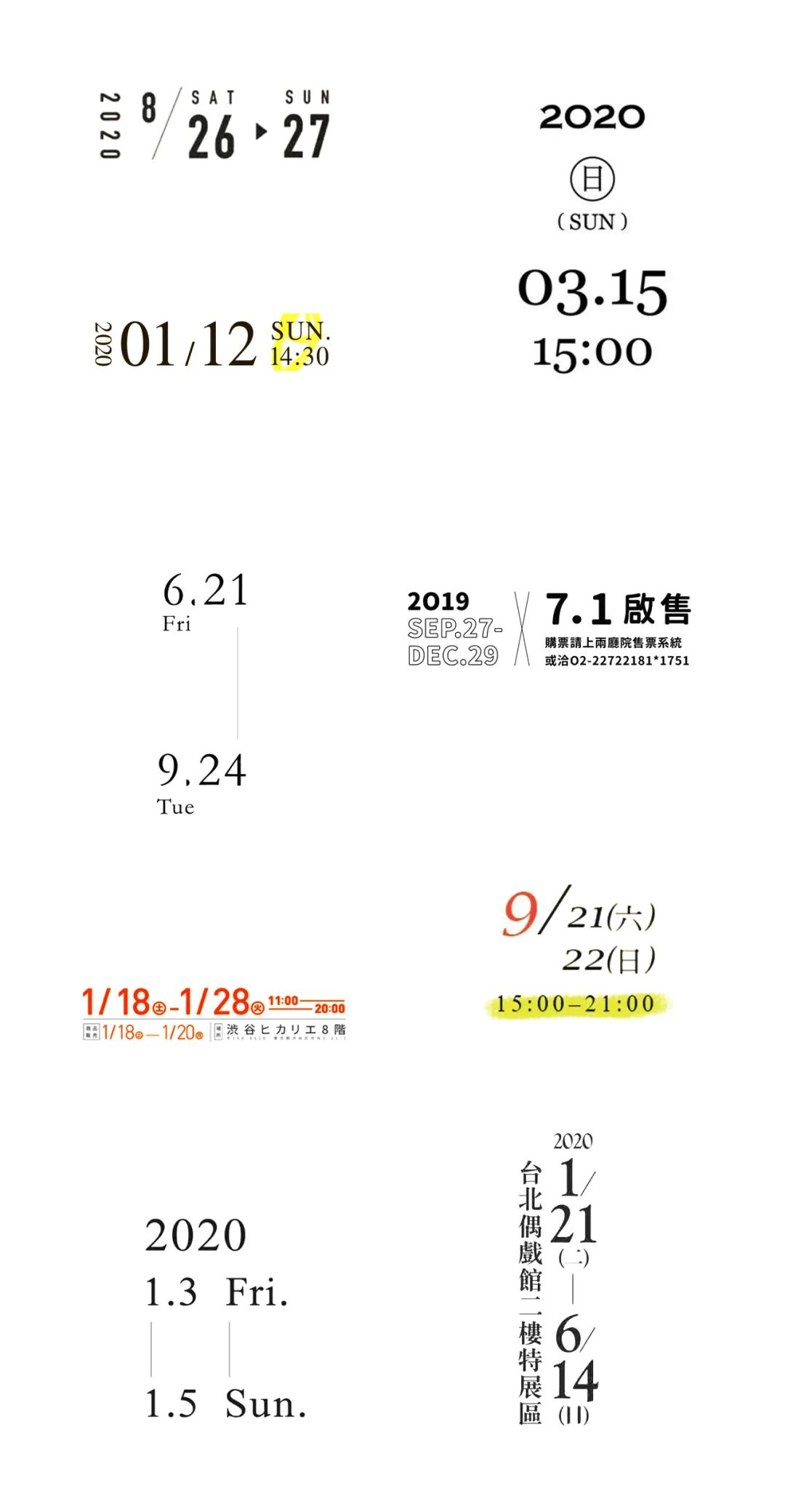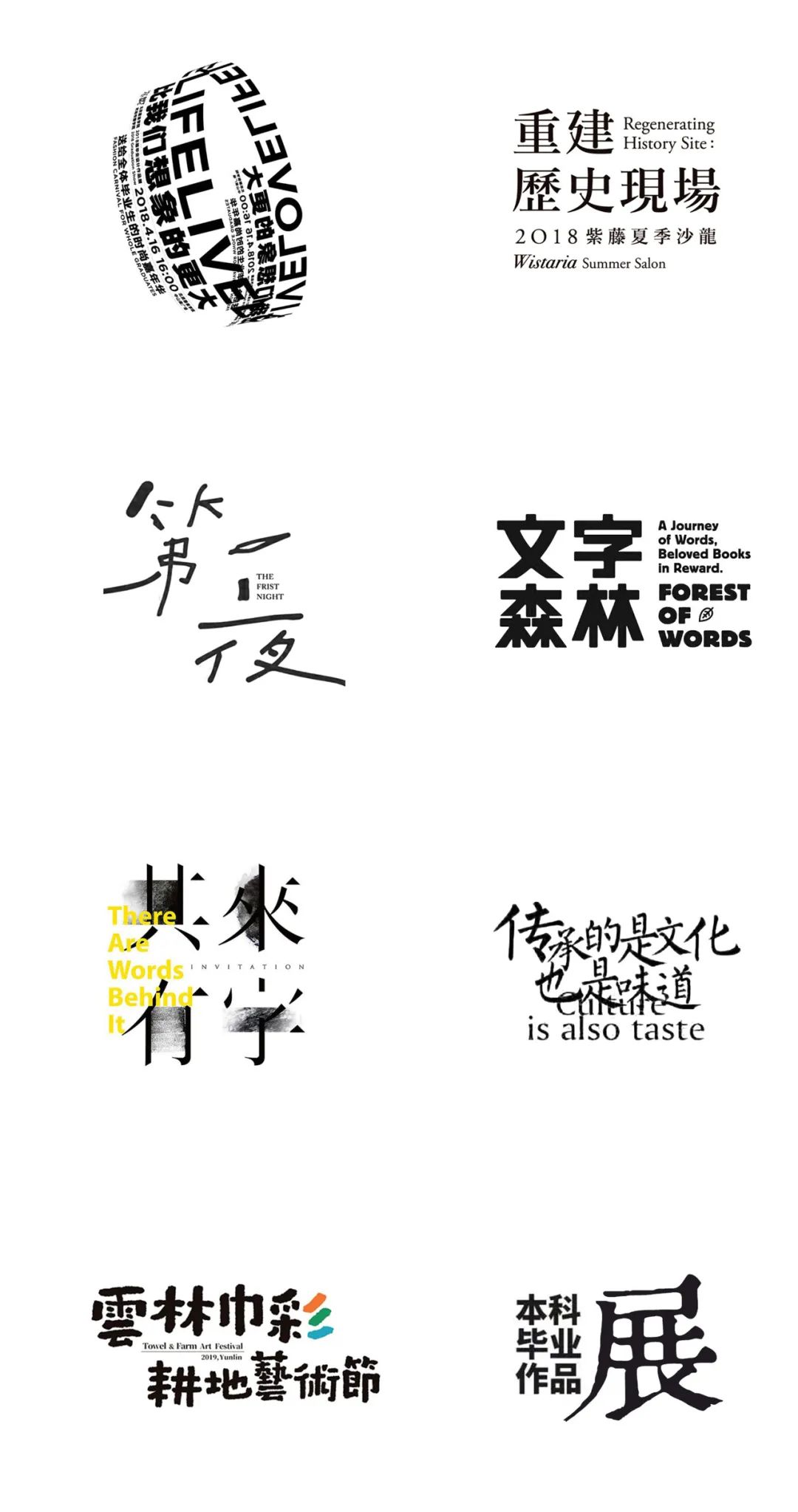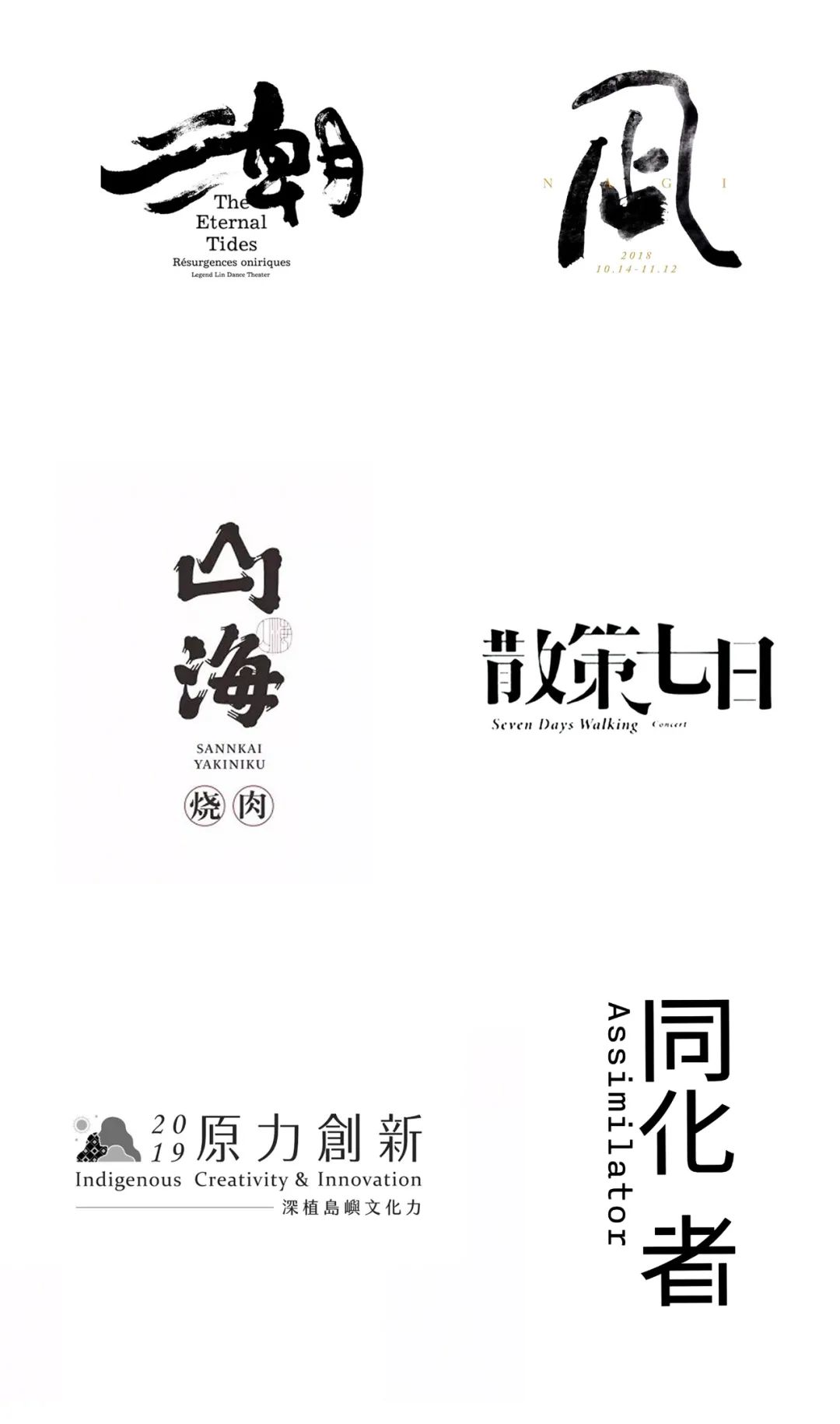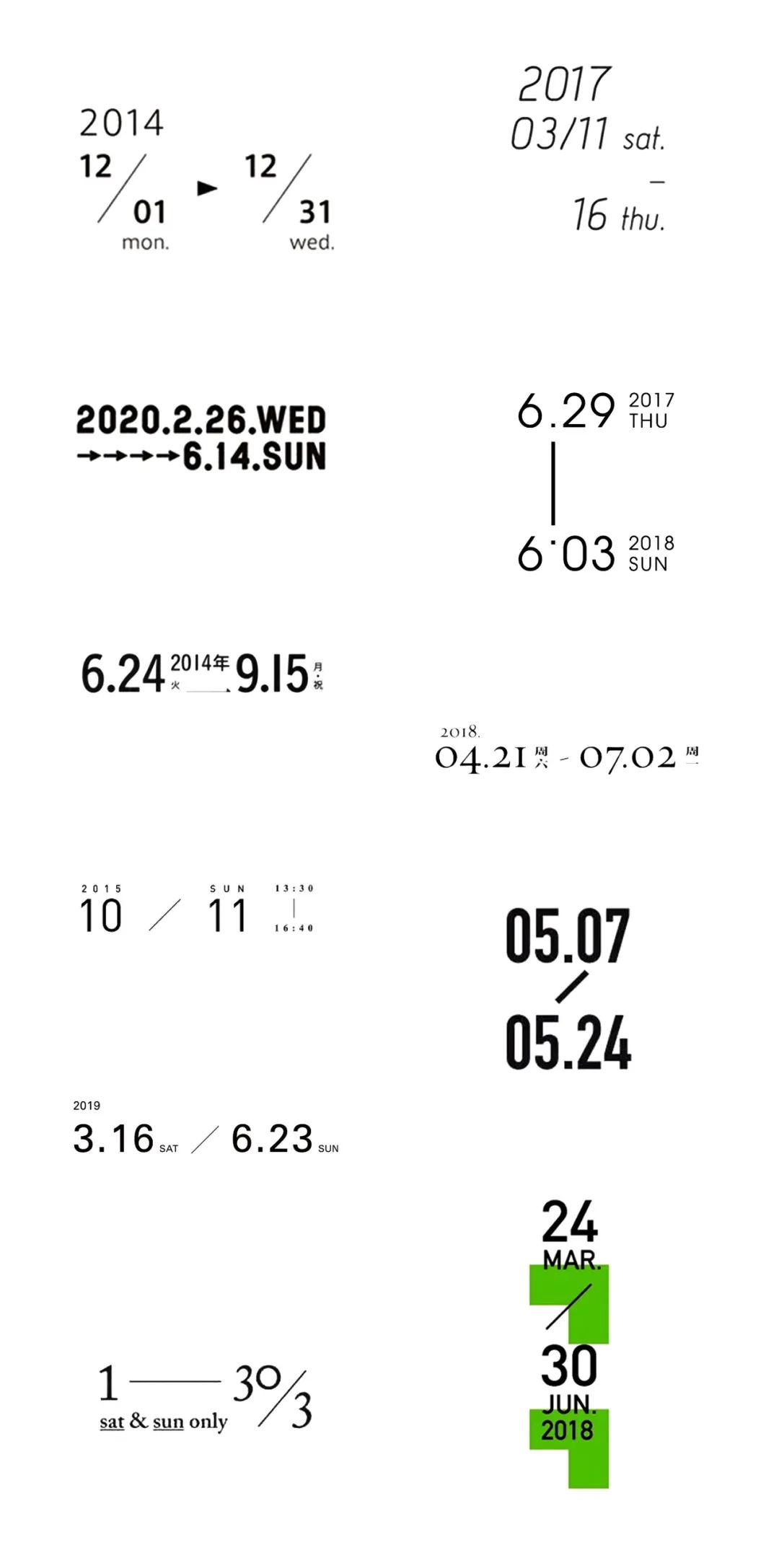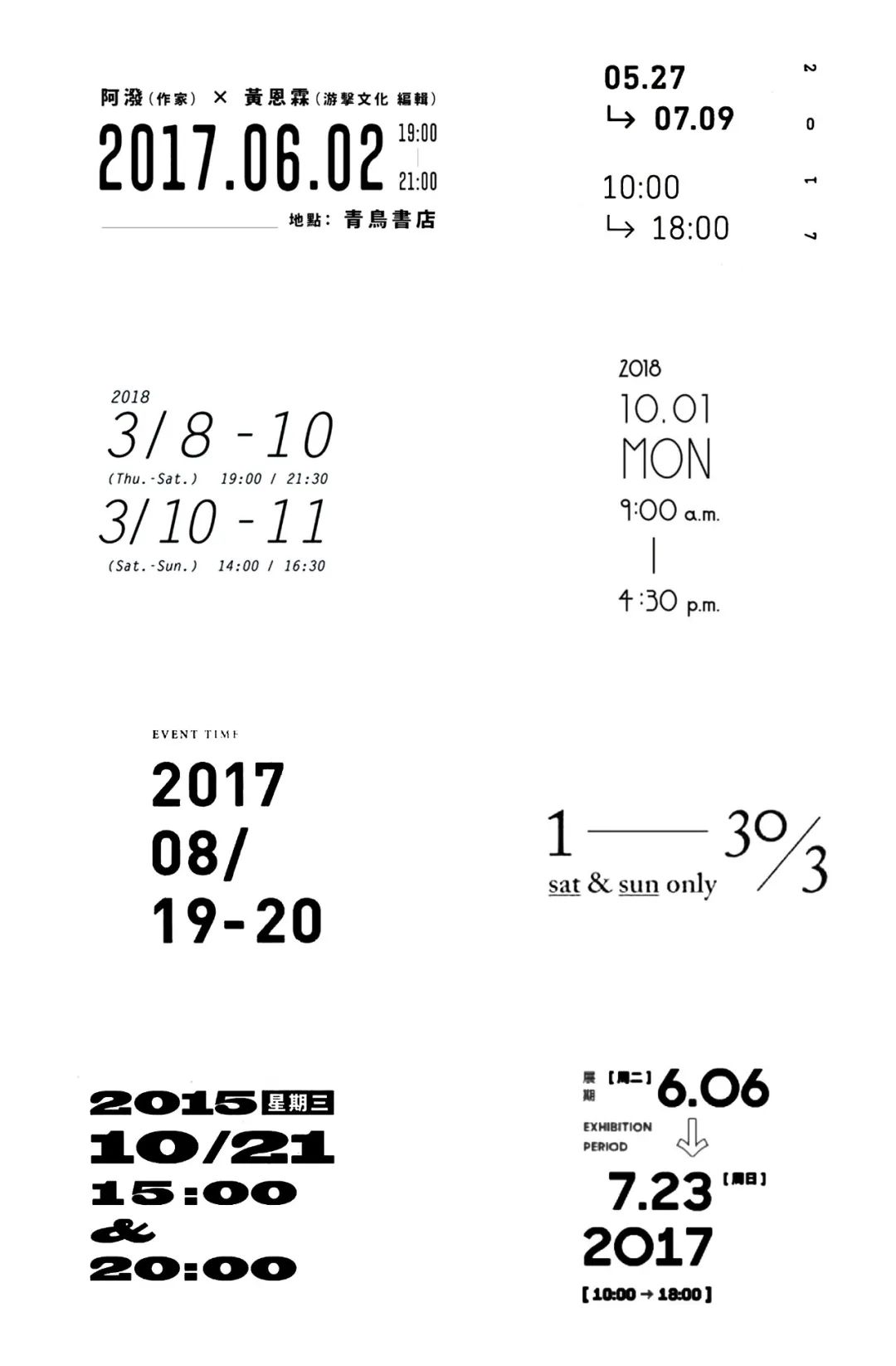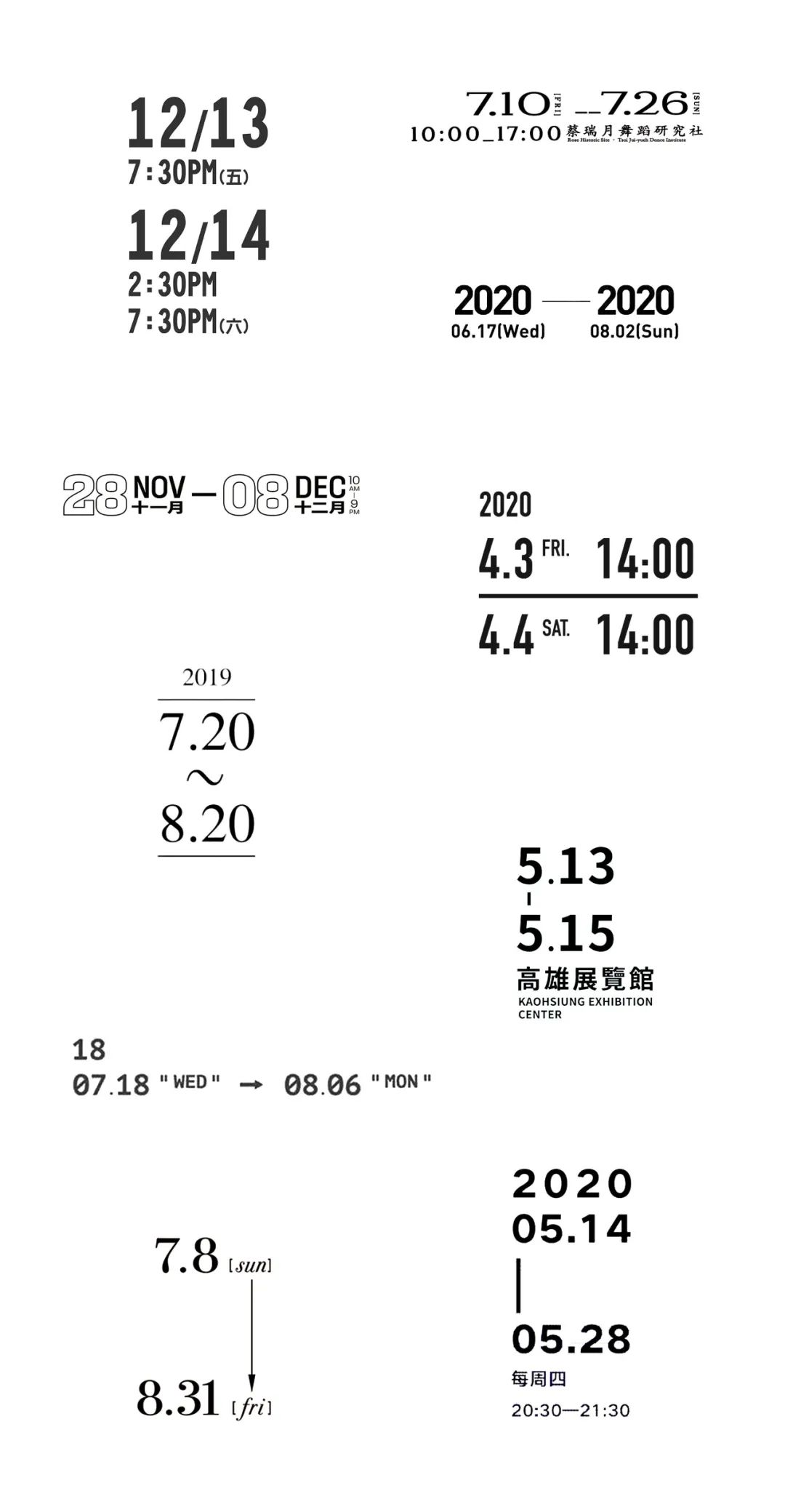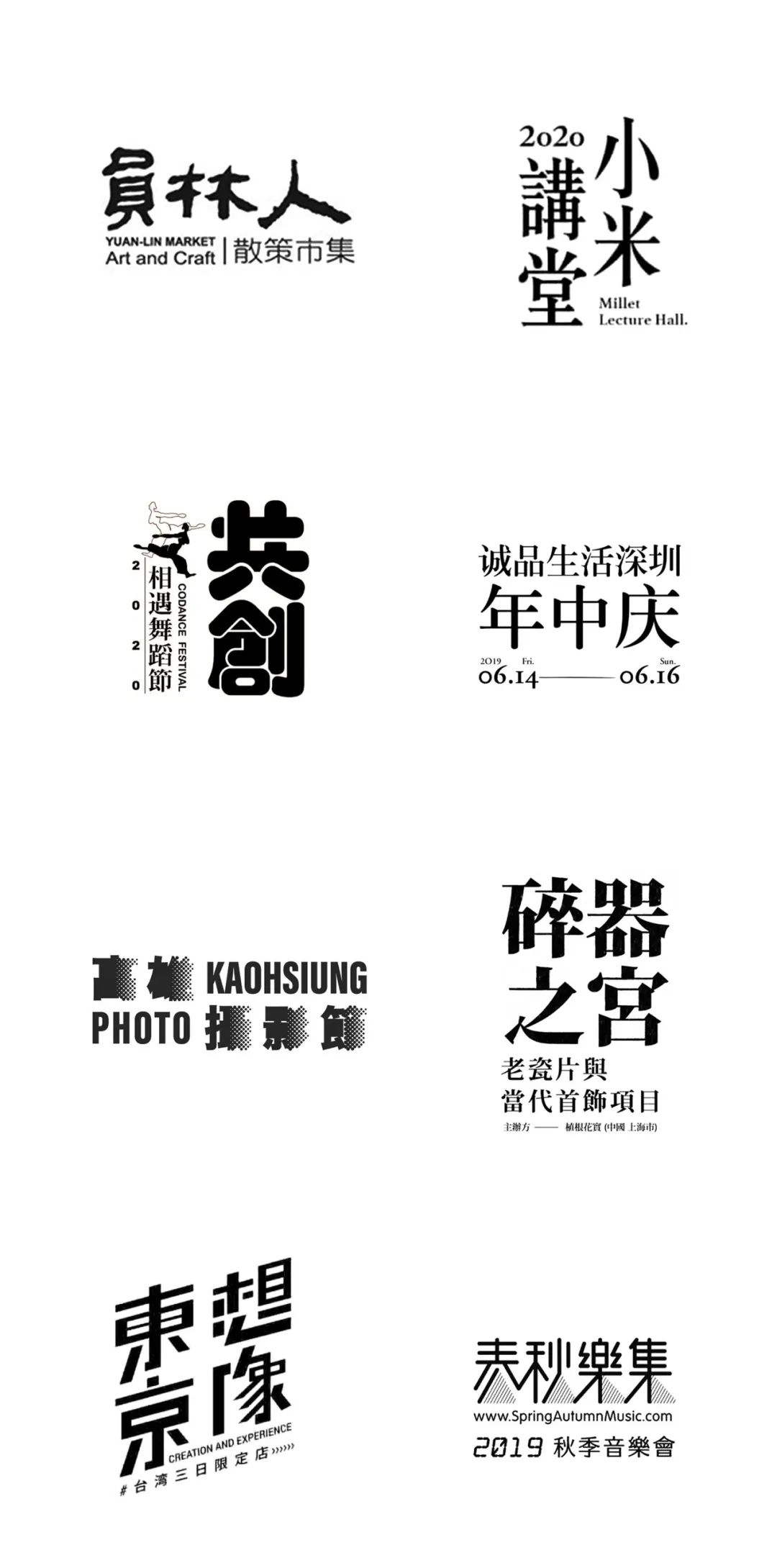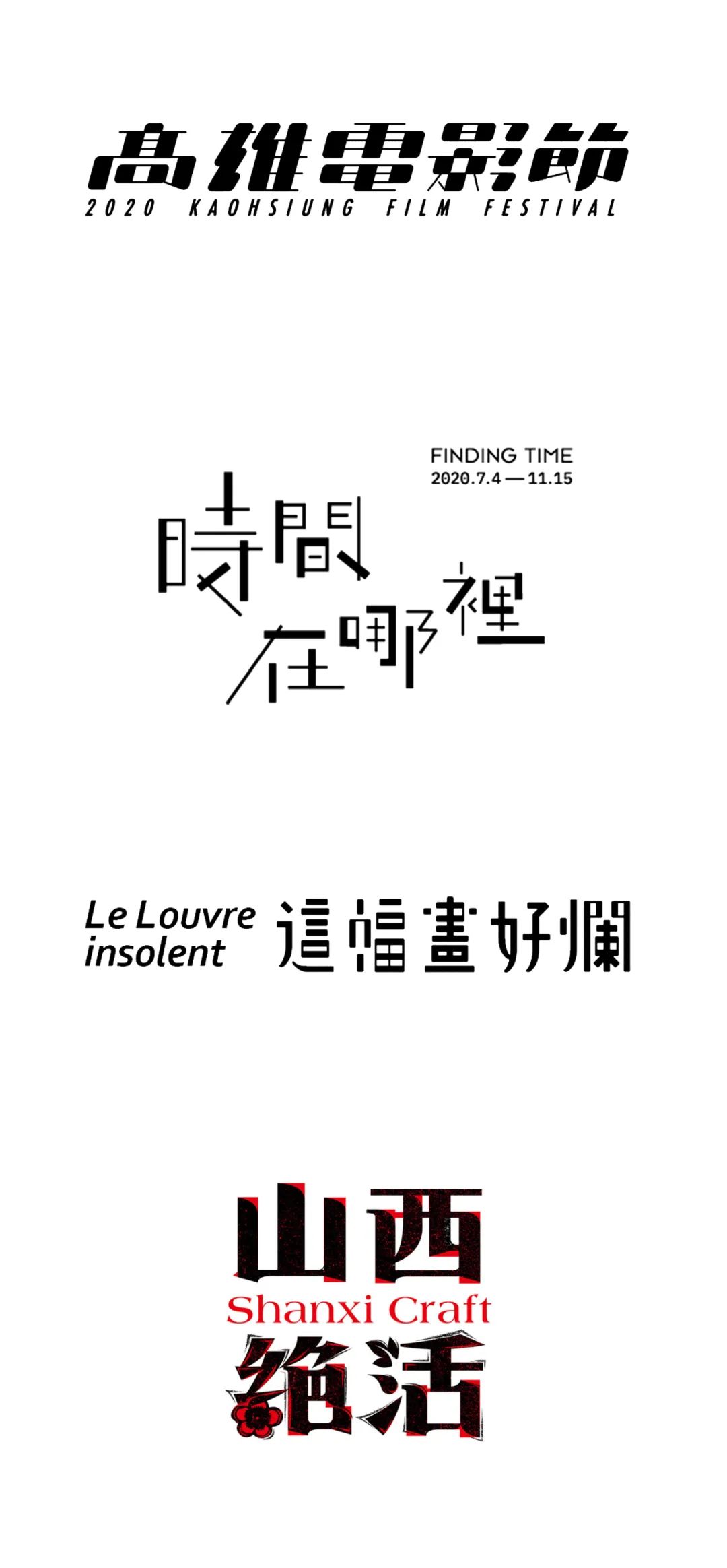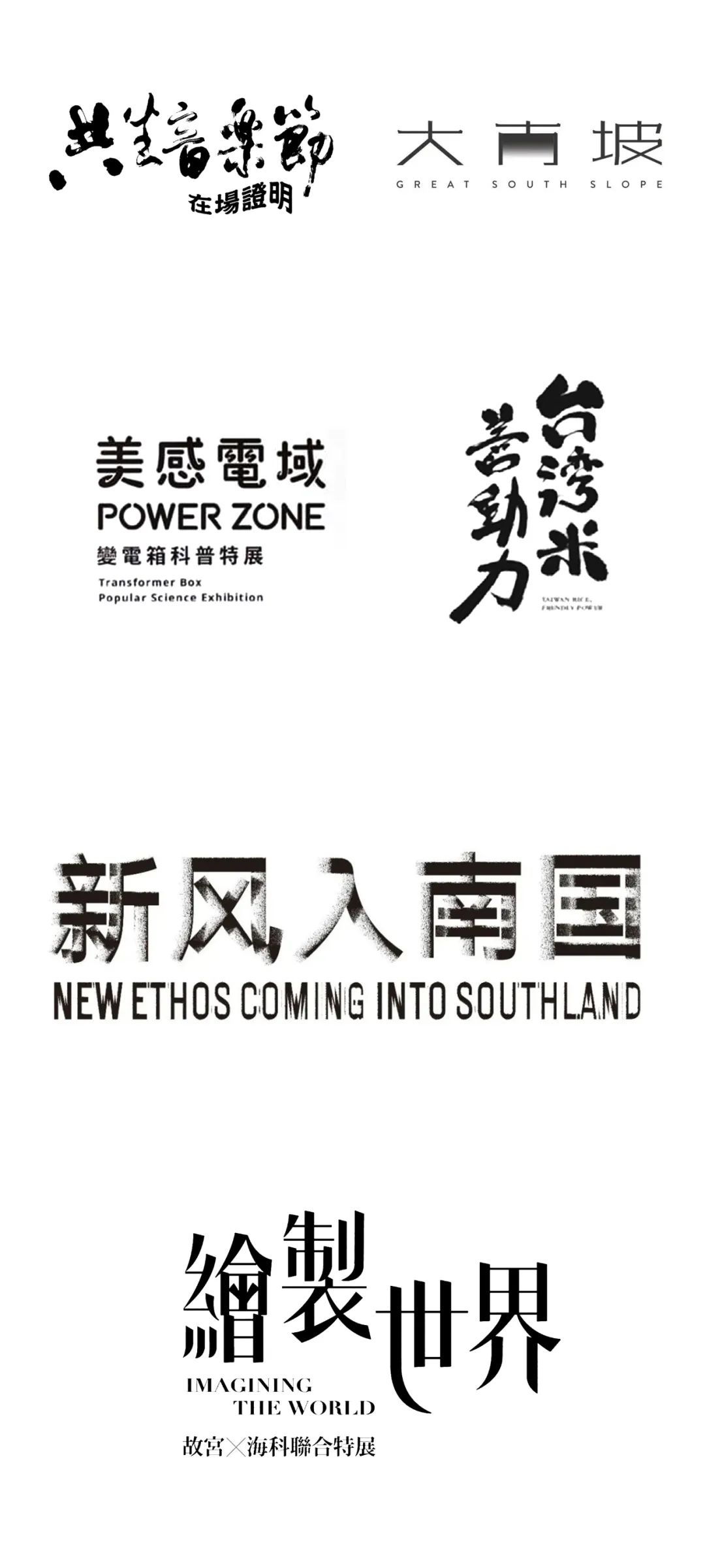
标题设计中的日期编排技巧,通通给你整理好!
有不少设计师觉得标题设计和日期编排很难,特别对于刚入门的设计师,不知如何下手。在进行文字编排之前,我们首先要理解文字的内容。我见过很多设计师只注重版式美观而不关注文字内容,把文字一拿到手就开始编排,从不考虑文字在说什么。他们认为文字一定要服从于自己的感觉,反而这是不正确的设计方法。对于一篇文案稿,如果我们不去理解它表述的内容,就很容易本末倒置。这次我整理了常见的标题设计和日期编排的参考,应该能给你带来不少的灵感。你会发现重组之后的标题和日期,层次感也会丰富起来。